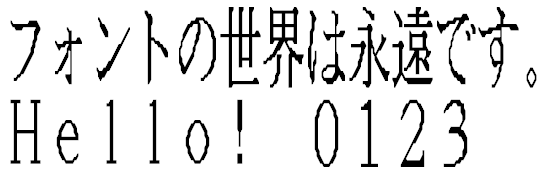
Zenフォントファミリー
- Googleによる日本語フォントコレクション
- Zen紅道
- Zen角ゴシックニュー(5 weight)
- Zen角ゴシックアンチック(5 weight)
- Zen丸ゴシック(5 weight)
- Zenオールド明朝(3 weight)
- Zenアンティーク
- Zenアンチックソフト
- 18組のデザイナーによる最大規模プロジェクト
- 画像は『Zen紅道』
- 「最大規模」を謳うなら楷書体とか作って欲しかった
- 角ゴシックを2種類作るなら
Monaspace Neon/Xenon Regular
- 7 weight
- 2 width
- 5 family
- Neon:neo-grotesque sans:サンセリフ体(ゴシック体)
- Argon:Humanist sans:「人間的」なデザイン
- Xenon:Slab serif:セリフ体(明朝体)
- Radon:Handwriting:手書き風味
- Krypton:Mechanical sans:縦・横・斜線からなるメカニカルなスタイル
- GitHubが開発したプログラミング用等幅フォント
- グリフ幅を変えずにレンダリングを調整する「Texture healing」機能を搭載
- 可変フォント(variable fonts)も用意
RFPナウ-GM/RFPナウ-MM
東風ゴシック/東風明朝
- 日本語フォントが不足していたLinux用に開発
- かなり高品質
- 第二水準まで網羅
- 2000年11月公開
- 当時無償の日本語フォントは貴重だった
- 参照した『渡邊フォント』の著作権問題で公開中止となる
さざなみゴシック/さざなみ明朝
- 旧『東風フォント代用品』
- 『和田研フォントキット』で自動生成されたフォント
- 問題のあった字体を書き換えてある
- 自動生成のため品質があまり良くない
梅ゴシック/梅明朝
- 2 weight
- 『さざなみフォント』派生書体
- プロポーショナル版あり
- 教科書体に近い「S」版あり
- 第四水準まで
- 字間が『MS ゴシック』『MS Pゴシック』『MS 明朝』『MS P明朝』と同じ
- 画像は英文が『梅P~』
梅UIゴシック
- 2 weight
- 字間が『MS UI Gothic』と同じ
IPAゴシック/明朝 Version 002.03
- 第四水準までのビットマップが入っている
- ゴシックと明朝で同じビットマップに見える…
FG平成角ゴシック体W5/FG平成明朝体W3
- FG平成角ゴシック体:4 weight
- FG平成明朝体:4 weight
- 4weight中2weightにビットマップが入っている
- 画像は英文が『FGP~』
FG教科書体NT-M
- ビットマップが入っている
- 教科書体のビットマップは貴重
- 画像は英文が『FGP教科書体NT-M』
TGothic-GT01/TMincho-GT01/TKaisho-GT01
- 「Tフォント(GTセット)」
- 36万字のフォントを作成
- 13ファイルに分けて収録
- 漢字の歴史上に現れる多数の漢字をできる限り網羅することが目標
- 利用の便を図り3書体(ゴシック体/明朝体/楷書体)を用意
TTEdit半角ゴシック/明朝
- IPA『IPAフォント』の文字幅を通常の半分にした書体
- 限られた領域に文字を詰め込むためのフォント
- やや可読性・視認性が犠牲に
TTEdit2/3ゴシック/明朝
- IPA『IPAフォント』の文字幅を通常の3分の2にした書体
- 限られた領域に文字を詰め込むためのフォント
- 読みやすさも確保されている
DRU05ゴシックH2V
- IPA『IPAフォント』のグリフを90度回転させたもの
- 横書きコンテンツを縦書きで読むためのフォント
- フォントが変更できる携帯端末で
- 縦書き→横書き用「V2H」もあり
TTEdit鏡文字ゴシック/明朝
- IPA『IPAフォント』を左右反転した書体
- 美容院などで鏡越しに表示したい張り紙に
- ゴム判の見本に
鏡文字Pゴシック/明朝-ランダム Regular
- IPA『IPAフォント』を改造
- 等幅版あり
- 各文字をランダムに反転、回転させた書体
- 非ランダム版あり
NTモトヤ新聞明朝2
- 紙面上での濃度むらが極めて少なく、可読性に優れた書体
- 日経新聞、及び大部分の地方新聞が採用
紫陽花明朝
- 旧字明朝体フォント